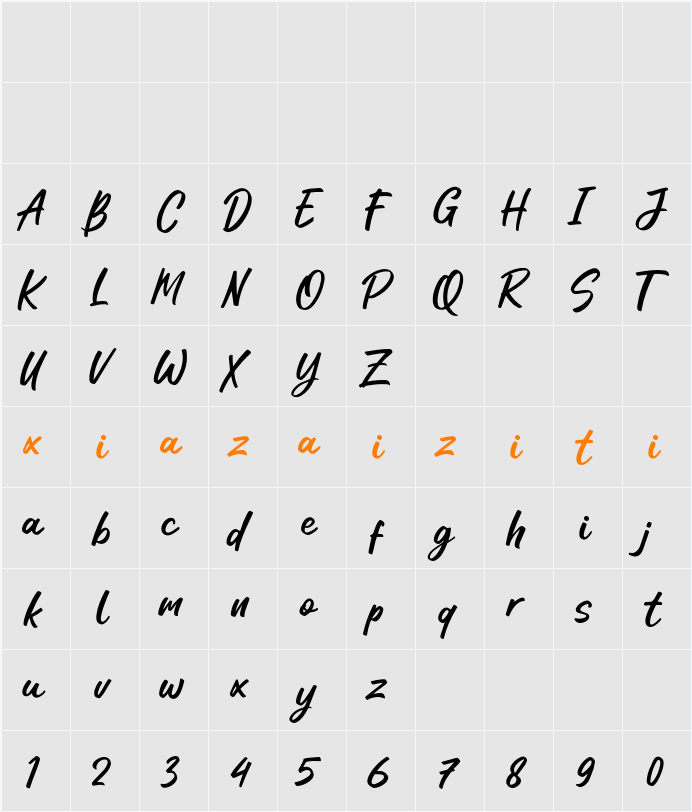
Windyear
Windyear,这款字体结构工整、笔画清晰,兼顾美观与易读性,适用于标题、正文、海报、包装、LOGO 等多种场景。字形优雅稳定,风格百搭耐看,适配日常排版与创意设计,让文字呈现更舒适、更具质感。Windyear一笔一画,皆是细节,以均衡的比例、流畅的线条打造舒适视觉体验,字形端正大气,风格简约现代。无论是商业设计、品牌宣传还是日常排版,都能轻松驾驭,让文字更有格调与力量。Windyear字体下载。
• 制造商: Khurasan
• 设计师: Khurasan